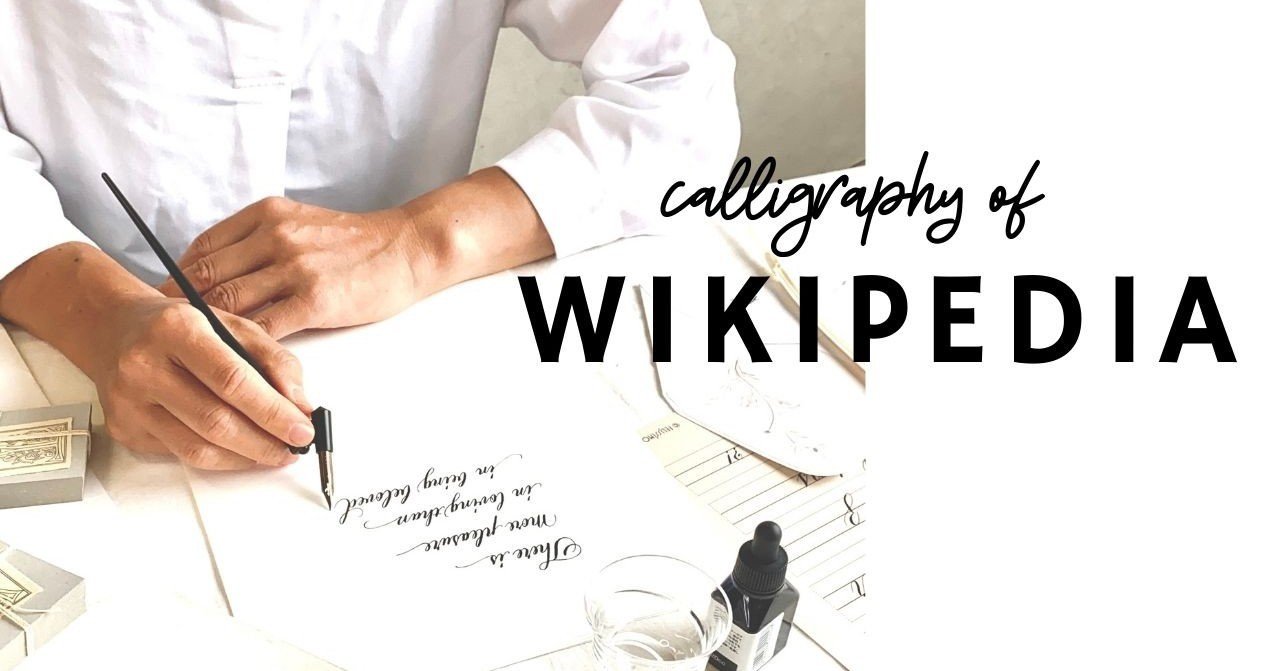
カリグラフィー 書体 種類
カリグラフィーフォントは、結婚式やイベントの招待状、オリジナルロゴのデザイン、宗教芸術、映画、テレビなどで広く使用されています。 Alejandro Paulが作った Burgues Script は、カリグラフィースタイルの典型的なフォント群です。.
カリグラフィー 書体 種類. カリグラフィーでは小文字の"x"の高さを基準にし、この高さを”Xハイト”と呼びます。 ”x”より高い文字(例:h,k,l)の目安を”アッセンダー”、 下にのびる文字(例:g,j,p,q)の目安を”ディッセンダー”と呼びます。 ※ ガイドラインとは?. カリグラフィー用のペン先(nib ニブ)で、カッパープレート以外の書体を書くためのブロードエッジドペン broadedged pen という幅広タイプのもので代表的なものを紹介します。 慣れない内は違いなどほとんど感じない(判らない)ですが、熟達するに連れて結構書き味やコントロールのしやす. 日本語は「明朝体」「ゴシック体」「筆記体」などの代表的なものを紹介しています。 アルファベットでは「ひげ」のある「セリフ」、「ひげ」のない「サンセリフ」「筆記体」と日本語フォントとほぼ似かよった分け方をしています。 デザイナーズフォントでは、「かわいい」「かっこいい」「おもしろい」などテイスト別に分けています。 INDEXフォント.
書体のバリエーション 6書体『カリグラフィーブック いろいろな書体で彩るウエディング』小田原真喜子 雄鶏社 掲載書体. 注意事項:本は2種類あります 15書体『カリグラフィー&写本装飾の魅力』河南美和子 マガジンランド 13/12/9 掲載書体;. 1 カリグラフィーの書体7選!定番人気のアルファベットとは 11 イタリック体;.
カリグラフィーはもともとペン先の角度が独特で、さらに慣れない万年筆で練習すれば挫折してしまうこともあるからです。 カリグラフィーとペン先の種類 カリグラフィーでは書体がいくつかありますが、代表的なものといえば. 6種類のカリグラフィーカードがつくれるコースです。 人気の「Happy Birthday」「Thank you」「Congratulations」の3つの言葉を、イタリック体とアンシャル体の2種類の書体で書きます。. カリグラフィー(希 καλλιγραφία, 英 calligraphy )とは、西洋や中東などにおける、文字を美しく見せるための手法。 字を美しく見せる書法という面は日本の書道など東洋の書と共通する部分があるが、筆記にペンまたはそれに類する道具を用いているため、毛筆を使用する書道とは表現さ.
カリグラフィー(Calligraphy)とは* 最近大流行のカリグラフィー(Calligraphy)* カリグラフィーとは、ギリシャ語で「美しい書き物」という意味。 専用のペンや筆ペンを使って、アルファベットを独特な美しいタッチで書く技術のことです♩. 注意事項:本は2種類あります 15書体『カリグラフィー&写本装飾の魅力』河南美和子 マガジンランド 13/12/9 掲載書体;. 書体のバリエーション 6書体『カリグラフィーブック いろいろな書体で彩るウエディング』小田原真喜子 雄鶏社 掲載書体.
各書体の特徴を調べてみました。 イタリック体 文字幅が狭く続けて書けるため、速く書けるイタリック体。 また字体はとても読みやすく、初心者の人が最初に学ぶのに適したカリグラフィーの基本的な書体。 流麗なデザインが特徴的。 ゴシック体. カリグラフィー用のペン先(nib ニブ)で、カッパープレート以外の書体を書くための ブロードエッジドペン broadedged pen という幅広タイプのもので代表的なものを紹介します。.